最早的汉字是商超出土的甲骨文,到秦朝时候的大篆、小篆,隶书。渐渐的出现了草书到狂草到楷书等等。随着时代的不断变换,用字环境需求的不同,研究出了简体字。广告字体就是根据商品的某些特点进而变化产生出来的字体,应用在广告上的字体一定是要具有辨识度、清晰度,让看到广告的人与字体达成共识吸引目光的,甚至是会想要寻找图片上的字体。今天就要给大家介绍几款集创意与内涵于一身的广告适用字体!
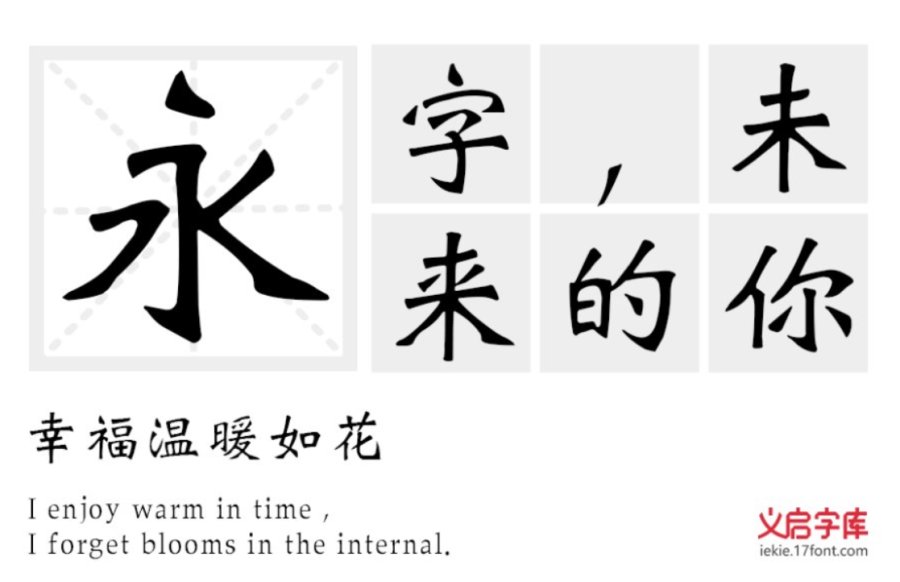
义启魏碑体:这是一款融合性很高的魏碑字体。融合兼顾所有魏碑特性,大量吸收了石刻、摩崖、墓志铭等碑帖特性。起笔方圆并济,撇捺加重刀切感。整体重心内敛,字字精神充满张力。剔除陈旧的审美,取而代之的是更为现代感的视觉风格。适用于现代、时尚主题的广告。
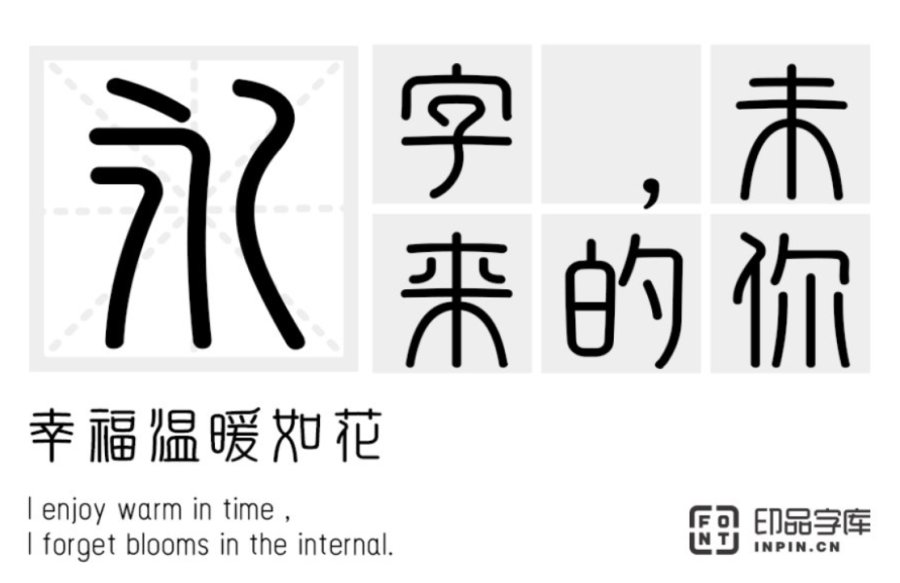
印品篆遇简:这款字体的灵感来源于篆书。虽然和现在的简体字有很大的区别,但是其字体非常优美,为了让现代人可以使用篆体般优美又易识别的字体,设计师设计出了这款字体。 此款字体笔画横平竖直,圆劲均匀,粗细基本一致。所有横画和竖画等距平行,所有笔画以圆为主,圆起圆收,方中寓圆,圆中有方,使转圆活,易于字体识别,富有奇趣。 适用于文艺、国风为主题的广告设计。
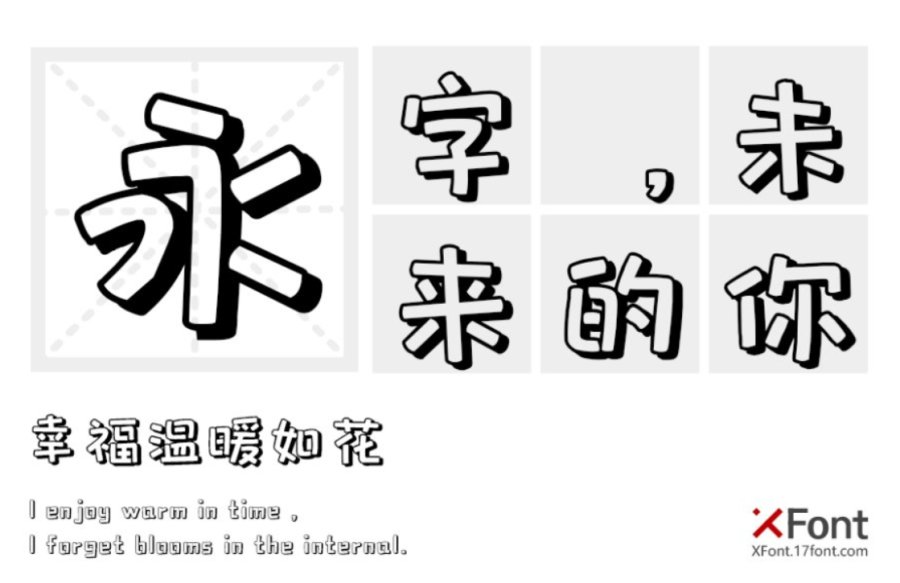
包图小白体:这款字体阐述出一种简单大方的字体性格。在字形笔画上去除了折笔的弧形,换以平直的笔画,竖弯钩转为竖折,同时弱化钩笔画,省去了许多笔画末尾的小尾巴,显得更加简单大方。整体形态采用了镂空的制作技巧,增加了字体的立体感,变换多样化。适用于青春、卡通、时尚主题的广告设计。(此款字体是为客户独家高端定制的,暂未开放授权)
一款字体同样可以适用于多种不同的风格,重要的是设计师如何把合适的字体准确地将产品气质传递给用户。